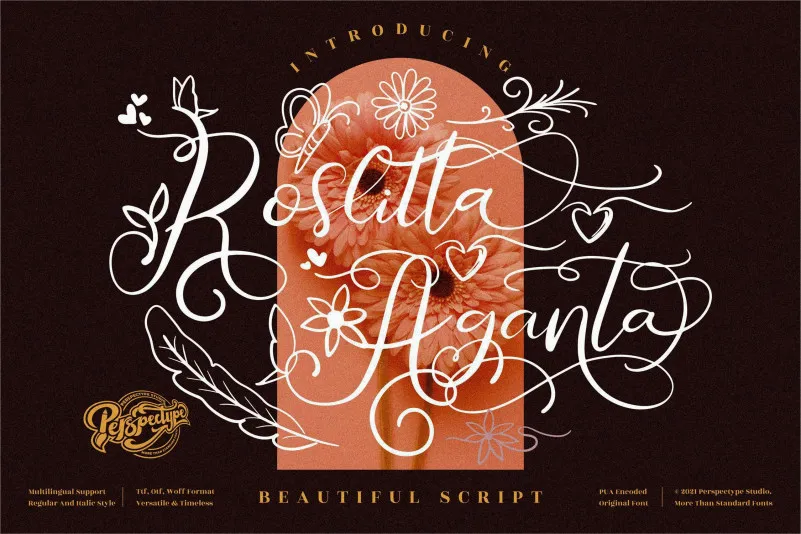
Roslitta Aganta é uma elegante fonte script que se destaca por sua sofisticação e modernidade, combinando perfeitamente os elementos do passado e do futuro. Perfeita para criar mensagens impactantes nos mais diversos formatos de comunicação, esta fonte atende desde a criação de logotipos e identidades visuais até projetos de casamento e posts nas redes sociais. O fato de ser PUA encoded significa que você terá acesso fácil aos todos os símbolos e swashes da fonte, proporcionando-lhe uma ampla gama de possibilidades para explorar suas capacidades únicas. Descubra o poder desta fonte inovadora em sua próxima projeto visual.